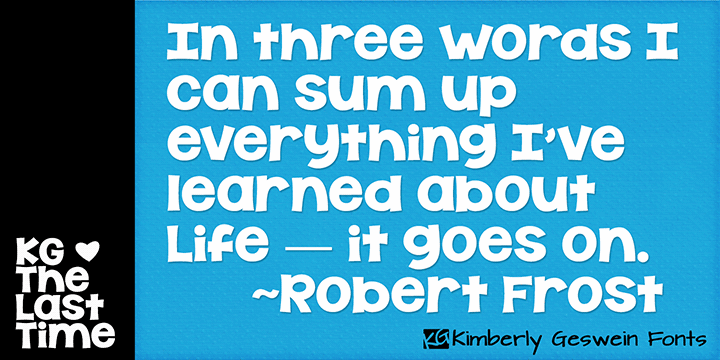
A fonte KG The Last Time oferece um toque divertido e peculiar ao seu design, apresentando letras em estilo sans serif que se destacam por sua estrutura afiada e robusta, formadas em uma única casca. Ela é ideal para um uso comercial, embora seja recomendado pagar pelos direitos de uso. Suas linhas retas e suas formas geométricas fazem dela uma escolha perfeita para elementos visuais que precisam ser chamativos e fortes sem perder seu caráter alegre. Para designers que procuram uma fonte que combine modernidade com um toque nostálgico, KG The Last Time é certamente uma opção interessante para incluir em qualquer projeto. Esta fonte tem tudo o que você precisa para destacar seu trabalho e se tornar uma escolha popular entre os profissionais do design.